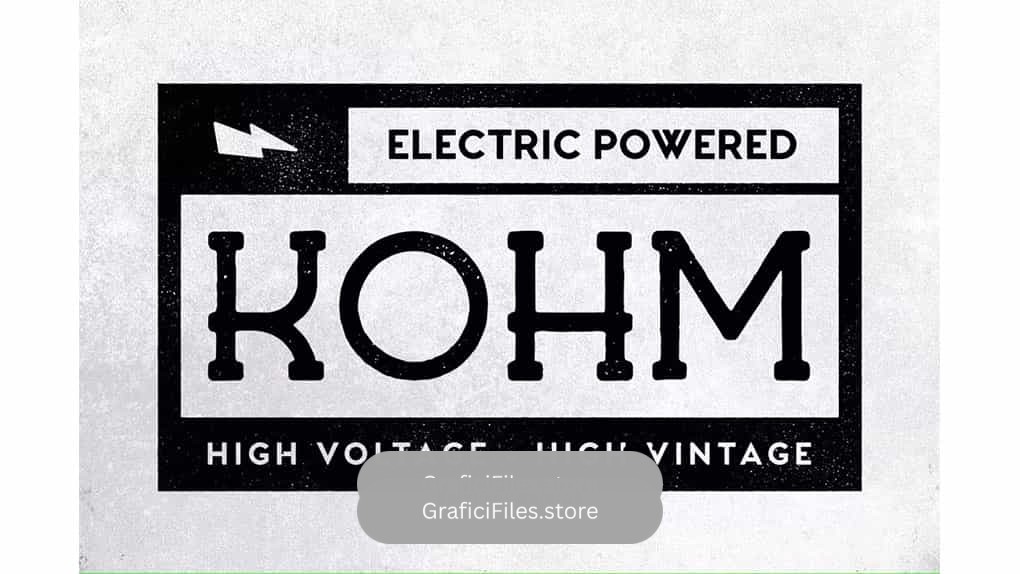
دانلود فونت انگلیسی Kohm – Vintage Font
فونت انگلیسی Kohm : این مجموعه شامل یک فونت خشن کلاسیک به سبک serif است که برای لوگو ها، پوستر ها، بسته بندی ها و … مناسب میباشد.
• عنوان مجموعه: Kohm – Vintage Font
• سبک: Serif
• فضا بین حروف: معمولی
• اندازه بهینه: بزرگ (نمایش / پوستر)